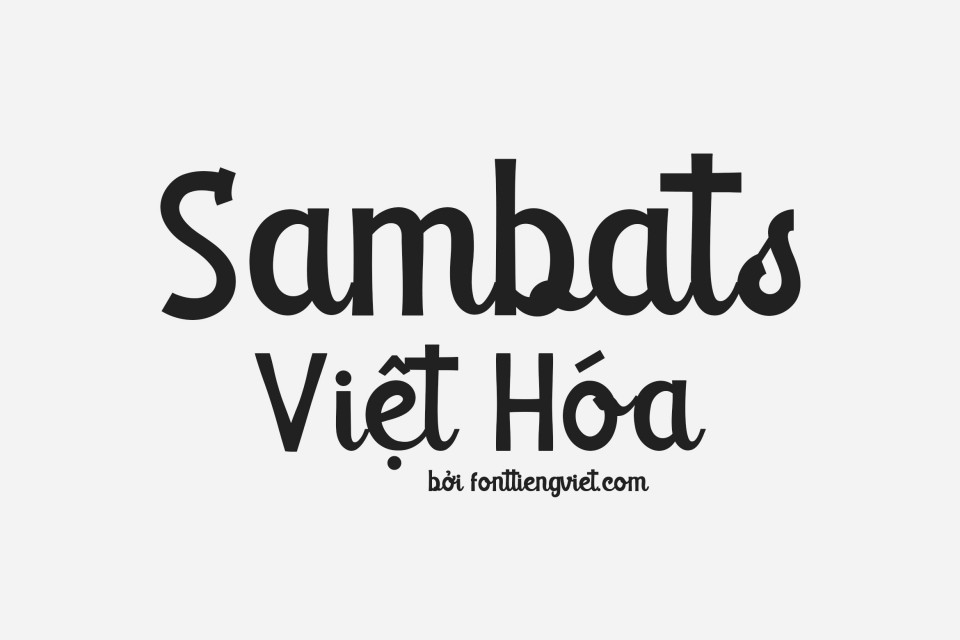
Font việt hóa 1FTV Sambats
Giới thiệu về Font việt hóa 1FTV Sambats
Trong thế giới thiết kế đồ họa hiện đại, việc tìm kiếm một bộ Font Miễn Phí chất lượng luôn là ưu tiên hàng đầu của các bạn học sinh và giáo viên. Font việt hóa 1FTV Sambats nổi lên như một lựa chọn hoàn hảo nhờ sự kết hợp tinh tế giữa nét chữ cổ điển và phong cách hiện đại. Đây là bộ phông chữ được tinh chỉnh kỹ lưỡng để phù hợp với bảng mã tiếng Việt, giúp người dùng dễ dàng tạo ra các sản phẩm truyền thông học đường ấn tượng mà không lo lỗi hiển thị hay thiếu dấu.
Đặc điểm nổi bật của Font việt hóa 1FTV Sambats
Phong cách thiết kế độc đáo
Font việt hóa 1FTV Sambats mang trong mình những đường nét thanh mảnh nhưng vô cùng dứt khoát. Cấu trúc chữ được thiết kế cân đối, tạo cảm giác dễ nhìn và chuyên nghiệp. Điều này giúp bộ font cực kỳ phù hợp cho các tiêu đề báo tường, bìa giáo án hoặc các bài thuyết trình PowerPoint tại trường học.
Khả năng ứng dụng linh hoạt
Không chỉ giới hạn trong môi trường giáo dục, bộ phông này còn được sử dụng rộng rãi trong thiết kế logo, poster sự kiện và thiệp mời. Font việt hóa 1FTV Sambats giúp thông điệp của bạn trở nên cá tính hơn, thu hút sự chú ý của người xem ngay từ cái nhìn đầu tiên. Đặc biệt, định dạng file nhẹ giúp quá trình cài đặt và sử dụng trên các phần mềm như Photoshop, Canva hay Word diễn ra mượt mà.